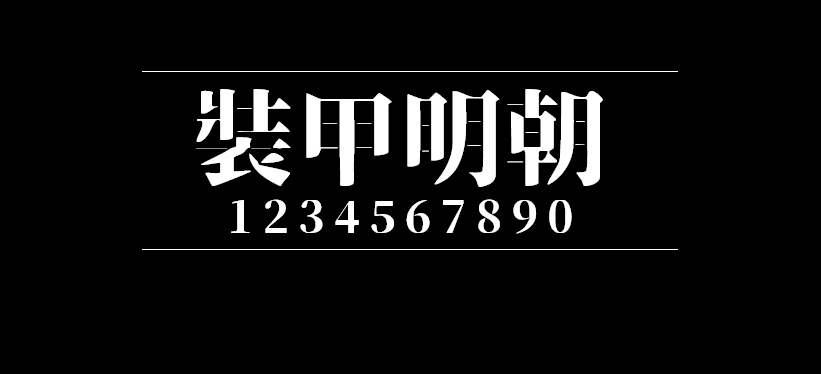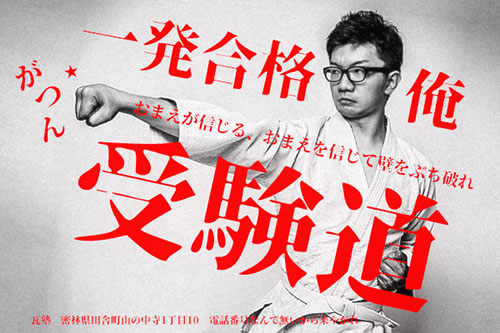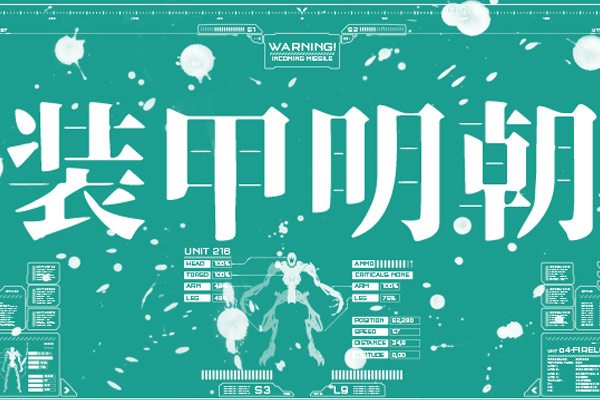
装甲明朝字体
「装甲明朝」看到这中文字体名称是不是觉得很霸气?如名称一样,字体风格硬朗有气派,以及拥有军队级的气氛、男人般凉意…… 若是拿来做越野车、大型装甲机车等玩具淘宝海报设计就非常适用了。
这是一款免费使用的中文字体,由日本网友从开源字体「思源宋体」改版而来,基于SIL Open Font License 1.1协议,但最终出来的效果却不大一样,装甲明朝体,将水平横线笔划修改得超细,在文字表现上,显得张力更强,十分霸气。
英文名称:Soukou Mincho